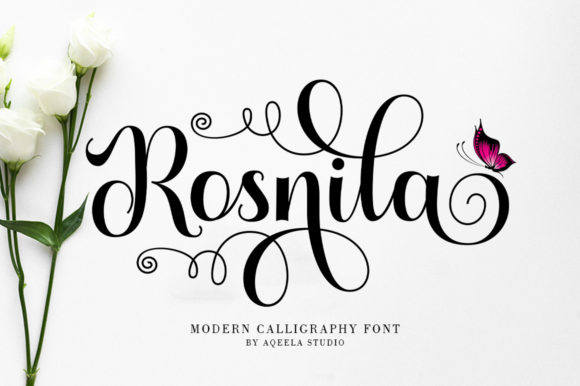
Роснила - это элегантный и сладкий рукописный шрифт с романтической искрой.
Используйте его, чтобы добавить этот особый завораживающий штрих к любой дизайнерской идее, которую только можно придумать!